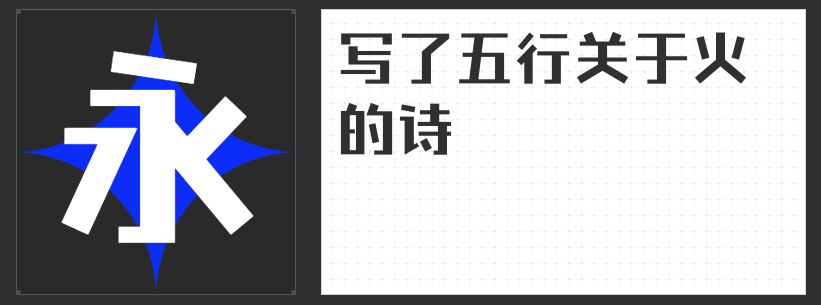
四款影视级标题字体推荐:用字形张力点燃视觉叙事
在影视设计的视觉语言中,标题字体是奠定风格基调的“第一帧画面”。它既要承载叙事主题的灵魂,又需以独特的形态瞬间抓住观众视线。以下四款专为影视场景打造的标题字体,以极具张力的字形设计与情感表达力,成为构建视觉叙事的利器。
一、造字侠伏魔简繁 传神
这款字体以传统书法为根基,却突破了常规笔触的克制。其笔画粗细对比强烈,横竖如刀削斧凿,而“勾、提、挑、捺”等细节则如飞白掠过纸面,既保留毛笔书写的苍劲感,又通过夸张的笔画形态强化视觉冲击。字形结构中正却不失灵动,单字收放自如,适合奇幻、武侠题材中需要传递力量与神秘感的场景。
二、造字侠磅礴简繁
若说“伏魔”是锋芒毕露的利刃,“磅礴”则是暗涌的浪潮。其运笔一波三折,笔画粗细如乐章起伏,转折处方圆结合,既有楷书的端庄,又带行书的洒脱。飞白效果的巧妙融入,让字体在厚重中透出呼吸感,仿佛墨迹未干便已凝固成永恒。这种动态平衡使其成为历史、战争题材的绝佳选择——无论是金戈铁马的战场,还是王朝更迭的史诗,都能通过字形传递出时间的厚重与命运的跌宕。
三、励字铁拳简 超级黑
当需要以绝对存在感压场时,“铁拳”是最佳答案。这款创意黑体以超粗笔画与宽大字面构建出“块面感”,折角圆润设计却让厚重中透出柔和,避免生硬感。其视觉冲击力如同铁拳出击,横扫千军,适合动作片、超级英雄题材中需要强化冲突感的标题设计。饱满的字形结构也能承载复杂背景而不失辨识度,是“大场面”的视觉锚点。
四、励字钧线黑简 大黑
全直线设计、完美斜度与利落转折,让“钧线黑”成为科技、悬疑题材的视觉符号。它摒弃过度装饰,以棱角对抗圆滑,用极简线条重构力量感。锐利的字形如数据洪流中的代码,又似未来都市的天际线,既能独立成为画面主角,也能与特效、光影无缝融合。其阅读舒适度与个性表达的平衡,更让长标题或动态字幕保持专业质感。
影视标题字体的选择,本质是视觉叙事策略的延伸。这四款字体或以墨韵传递文化深度,或以力量感点燃情绪,或以极简设计定义未来,为设计师提供了从传统到先锋的多元表达工具。当字形与光影、音效共振时,标题便不再是文字,而是开启故事的钥匙。